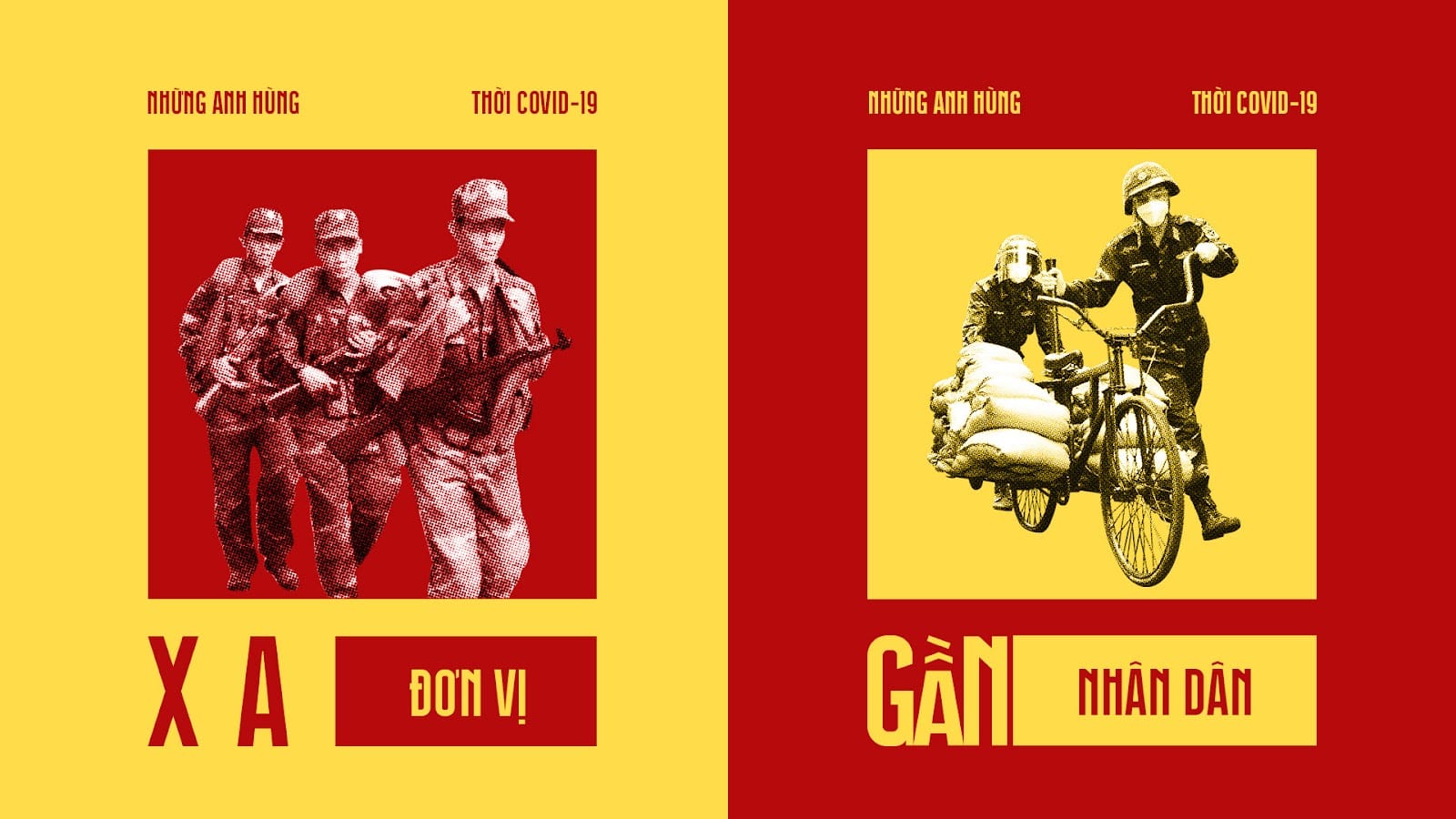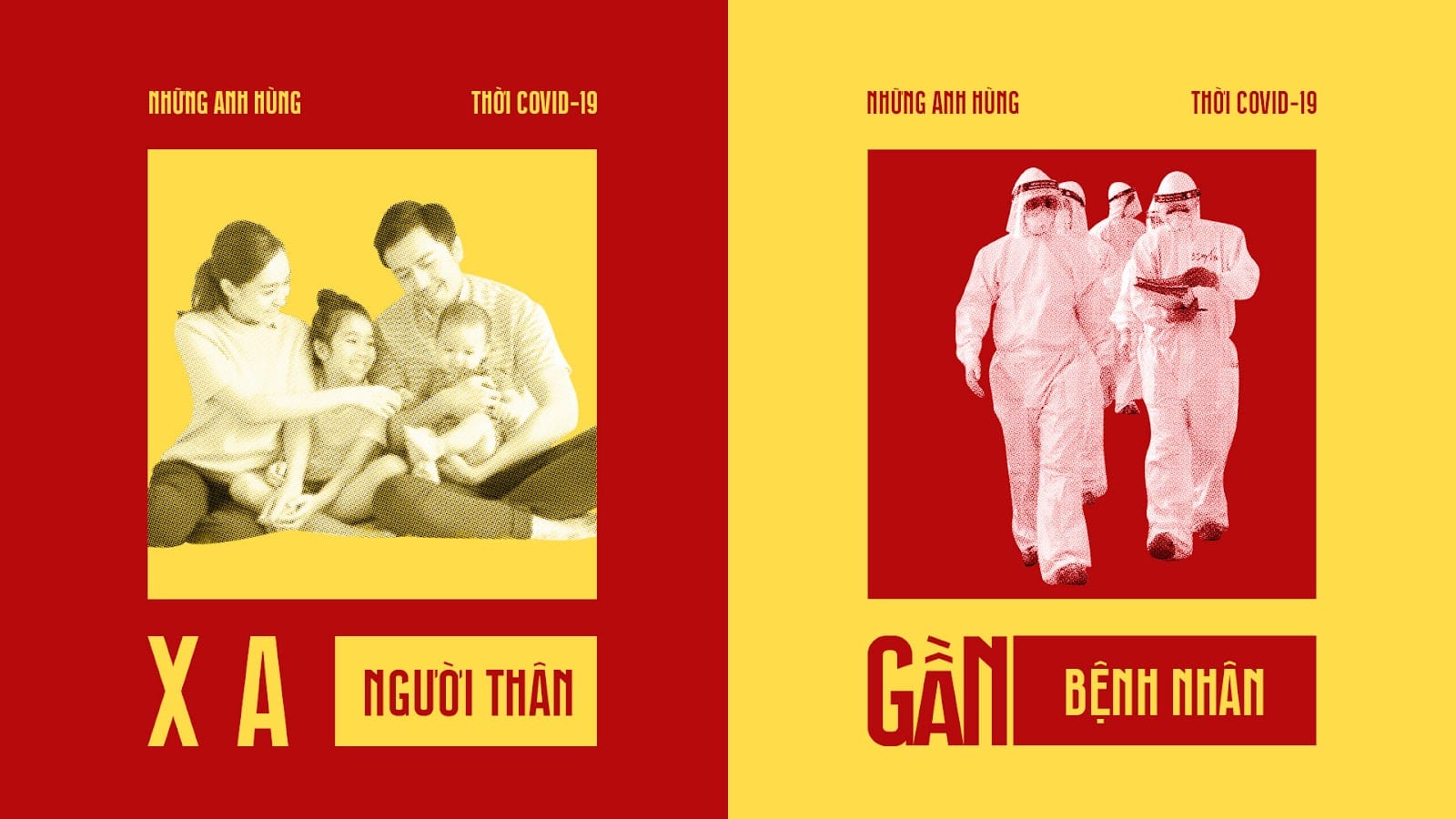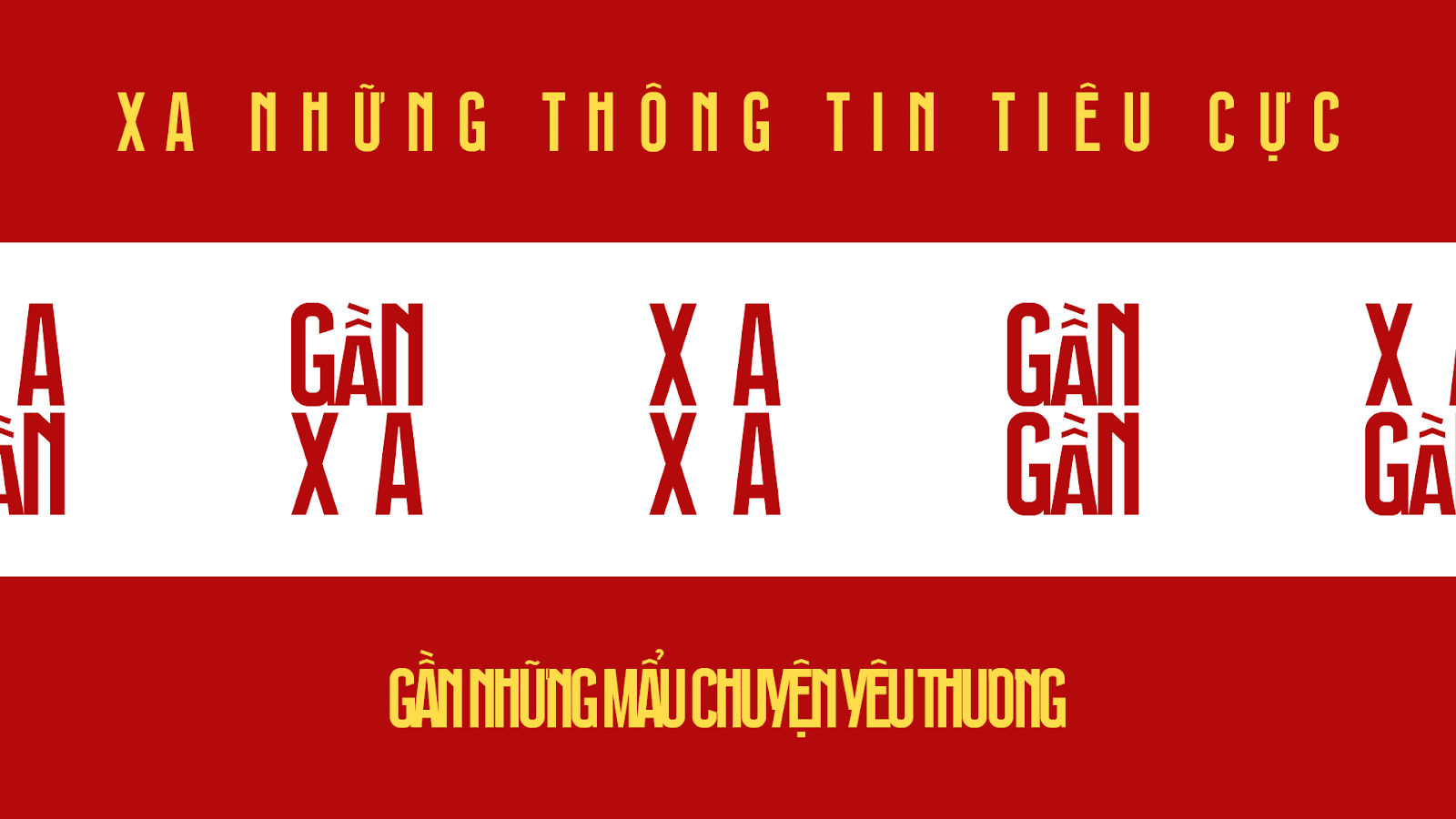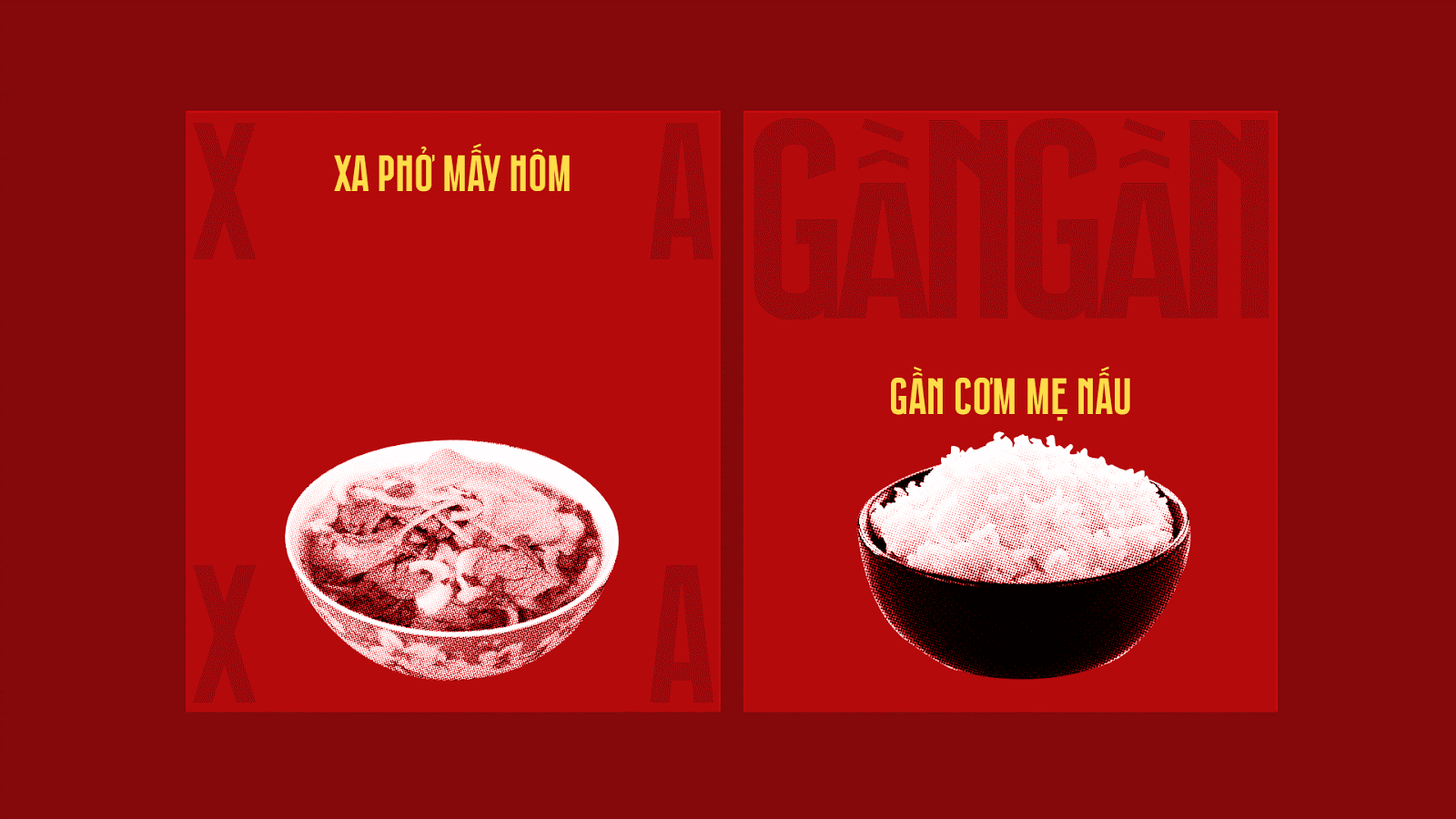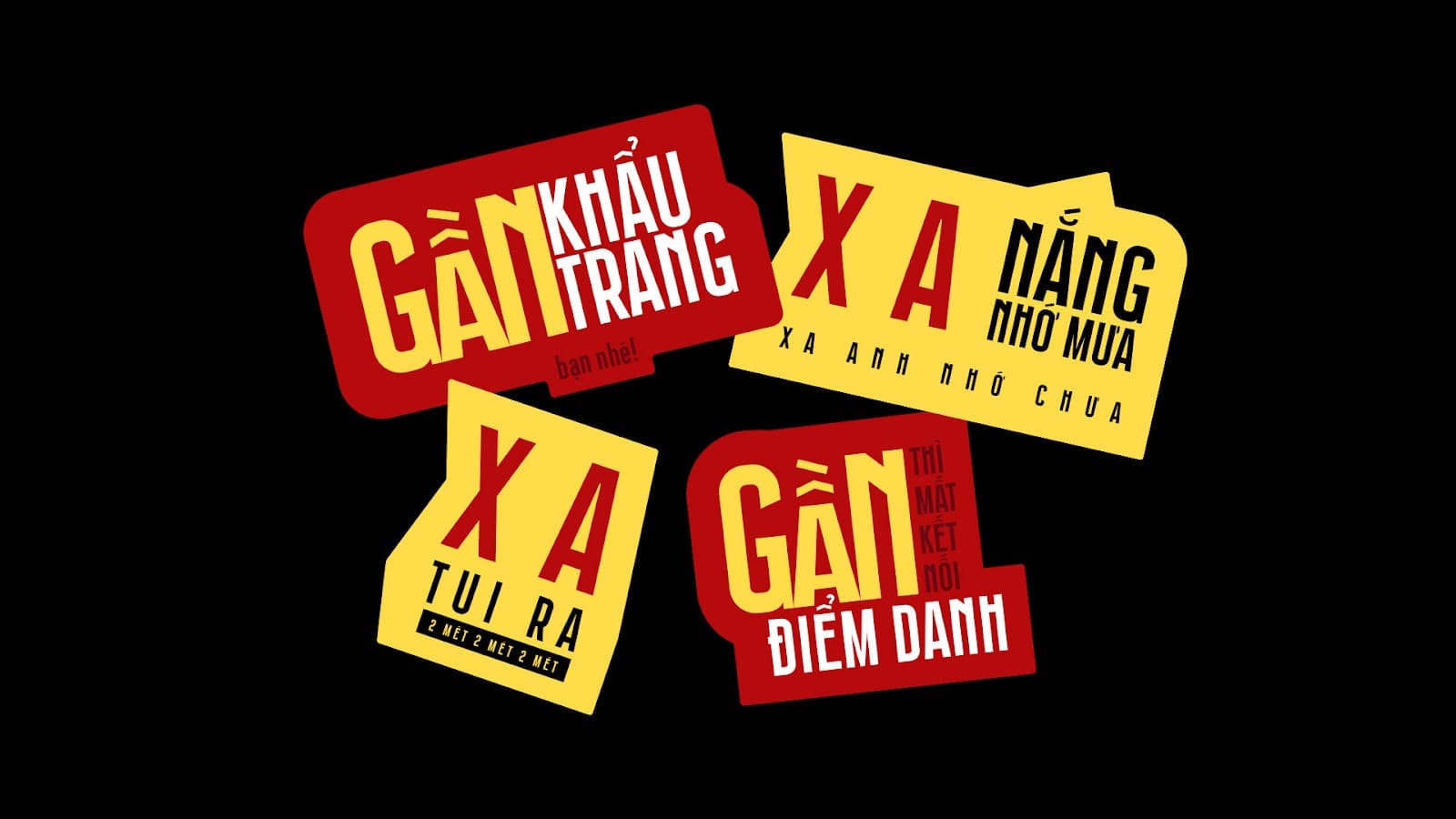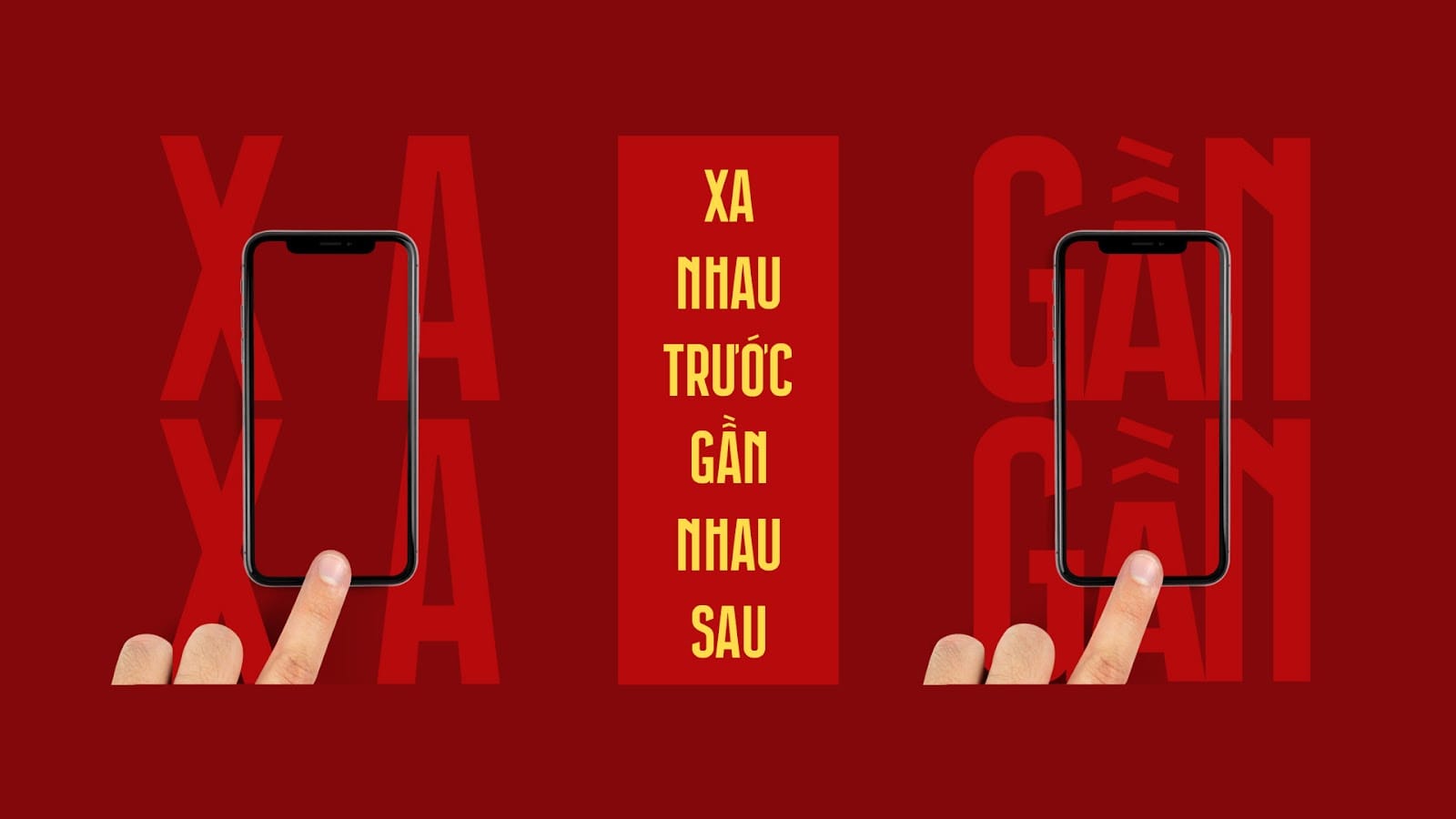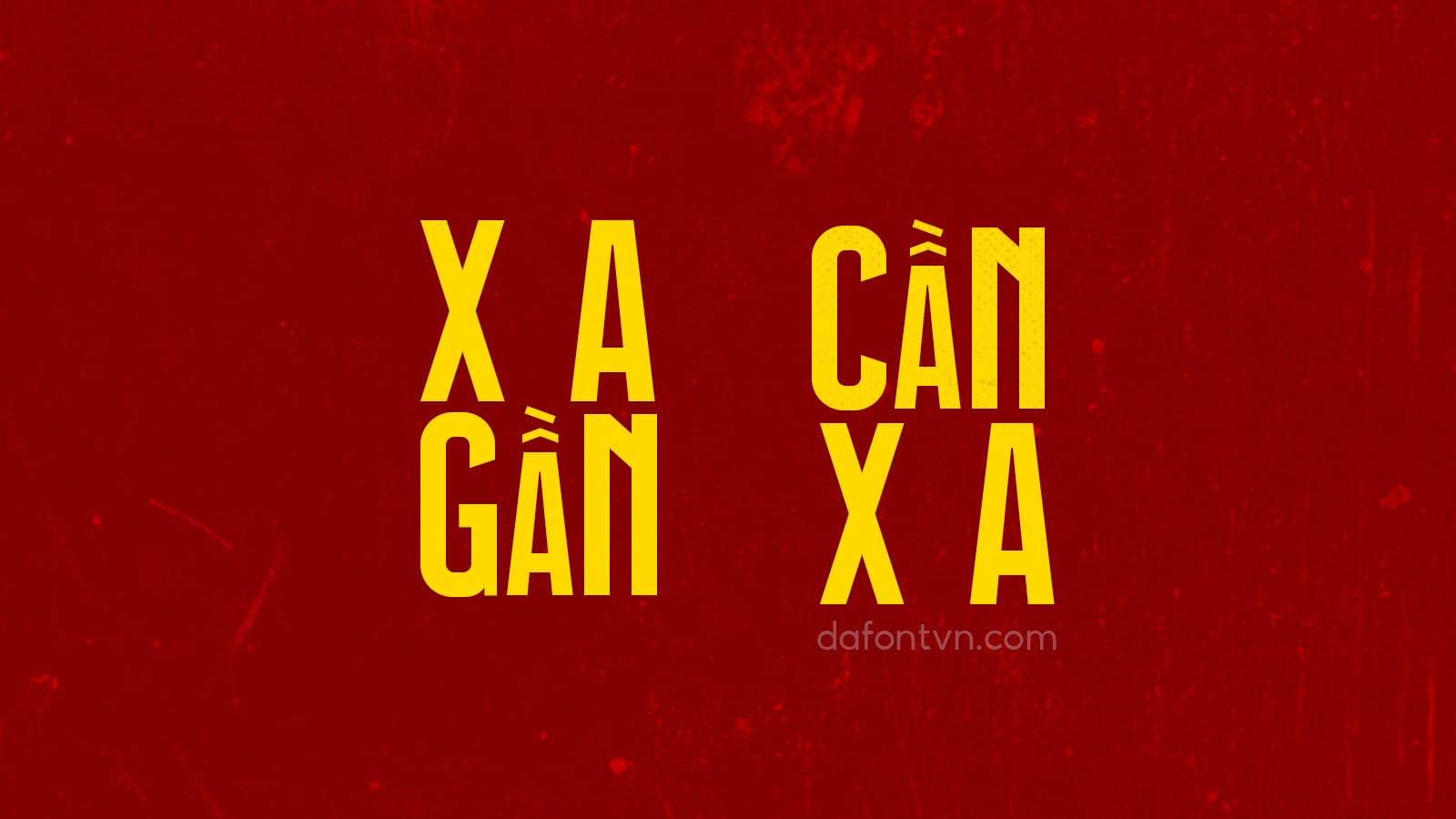
Danh Da (Đánh Đá) là một phông chữ Việt được thiết kế bởi Giang Nguyễn, font chữ Đanh Đá là sự kết hợp của nhiều tài liệu tham khảo khác nhau từ các tạp chí phụ nữa thế kỷ 20. Đanh Đá là kiểu san-serif với nét đậm, mang phong cách từ các thiết kế thời Pháp thuộc với sự cứng cáp tinh tế và và đậm chất Tuyên truyền.